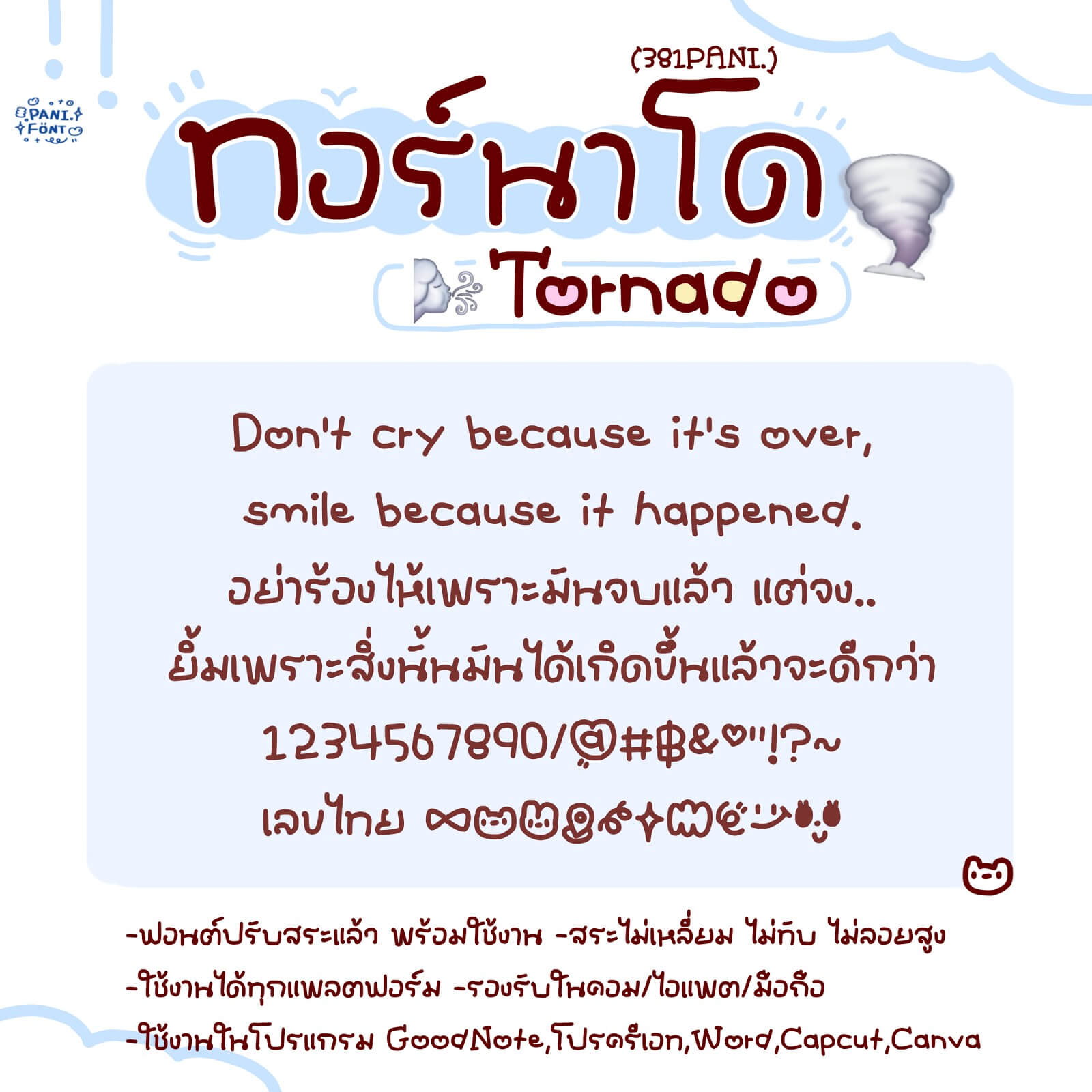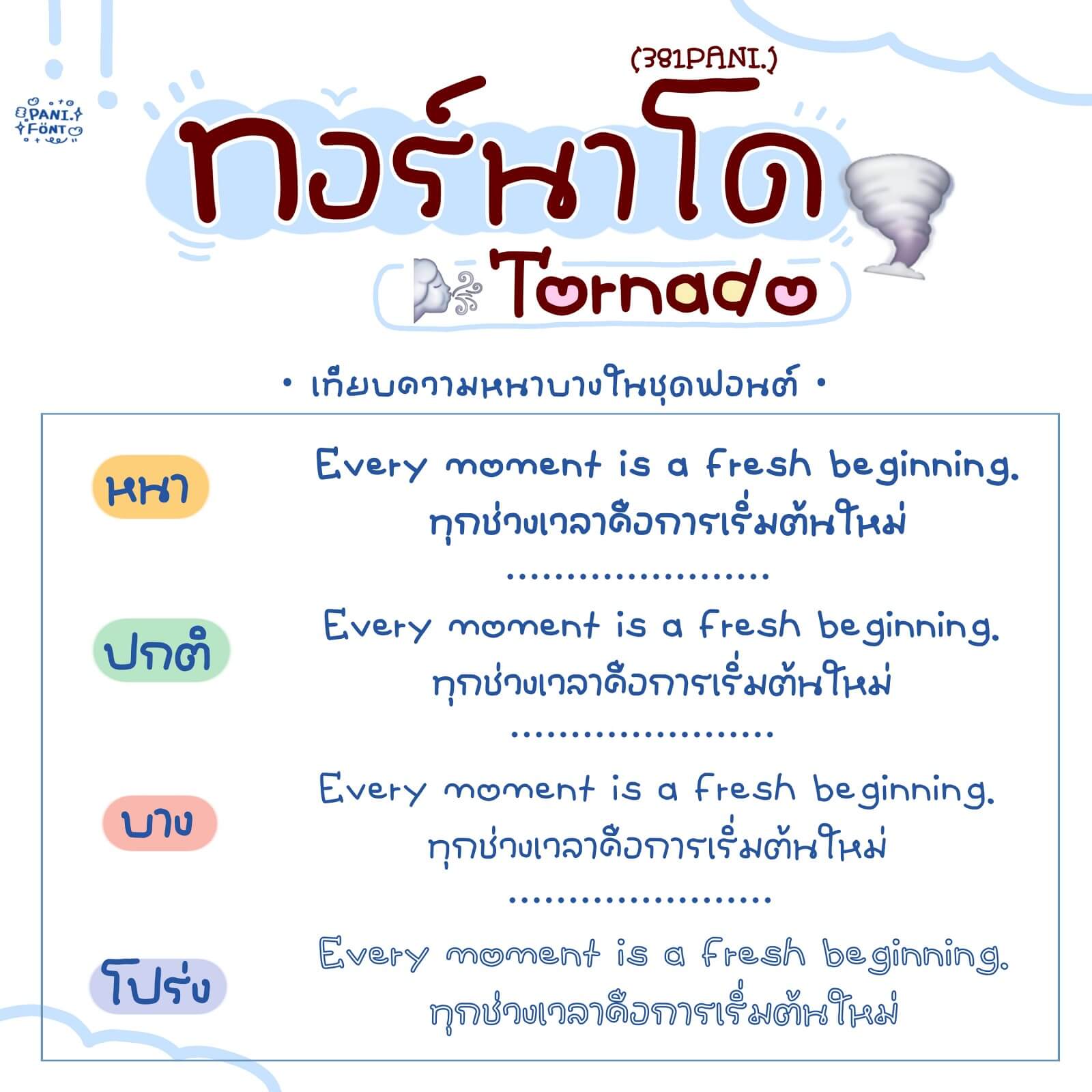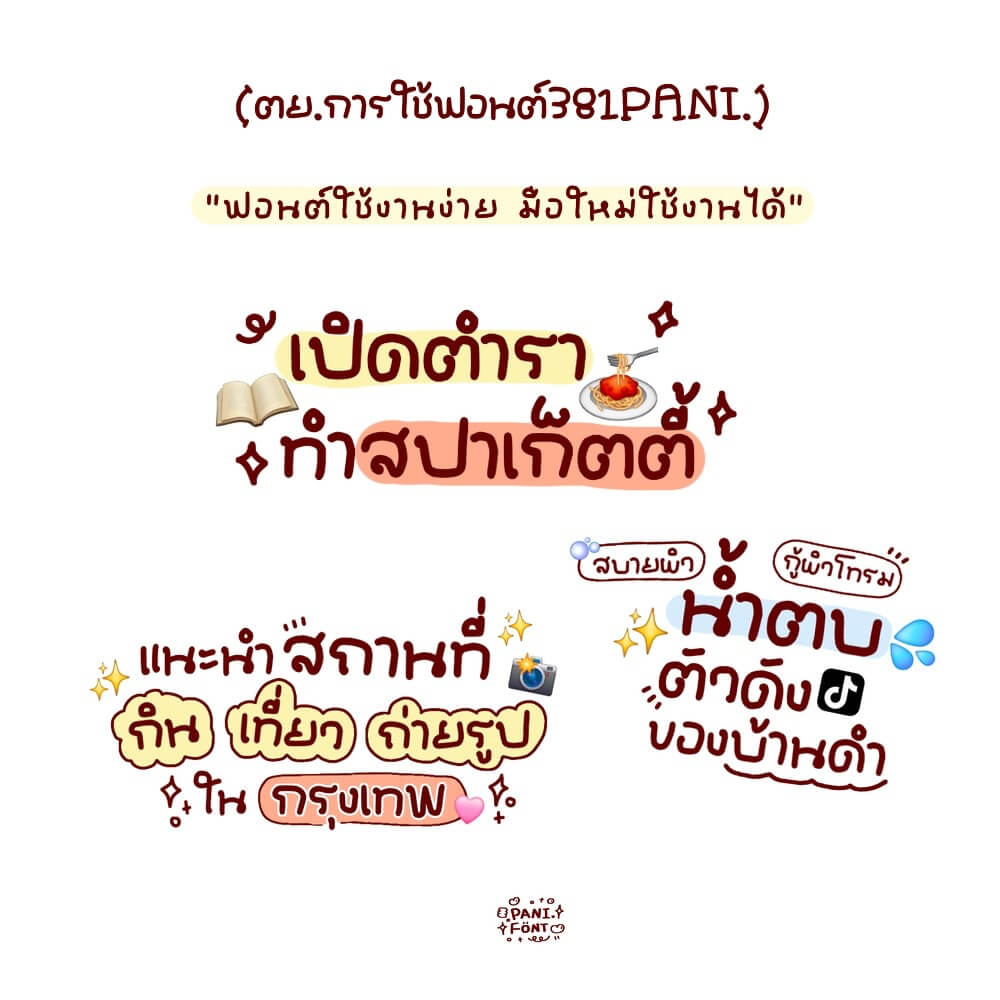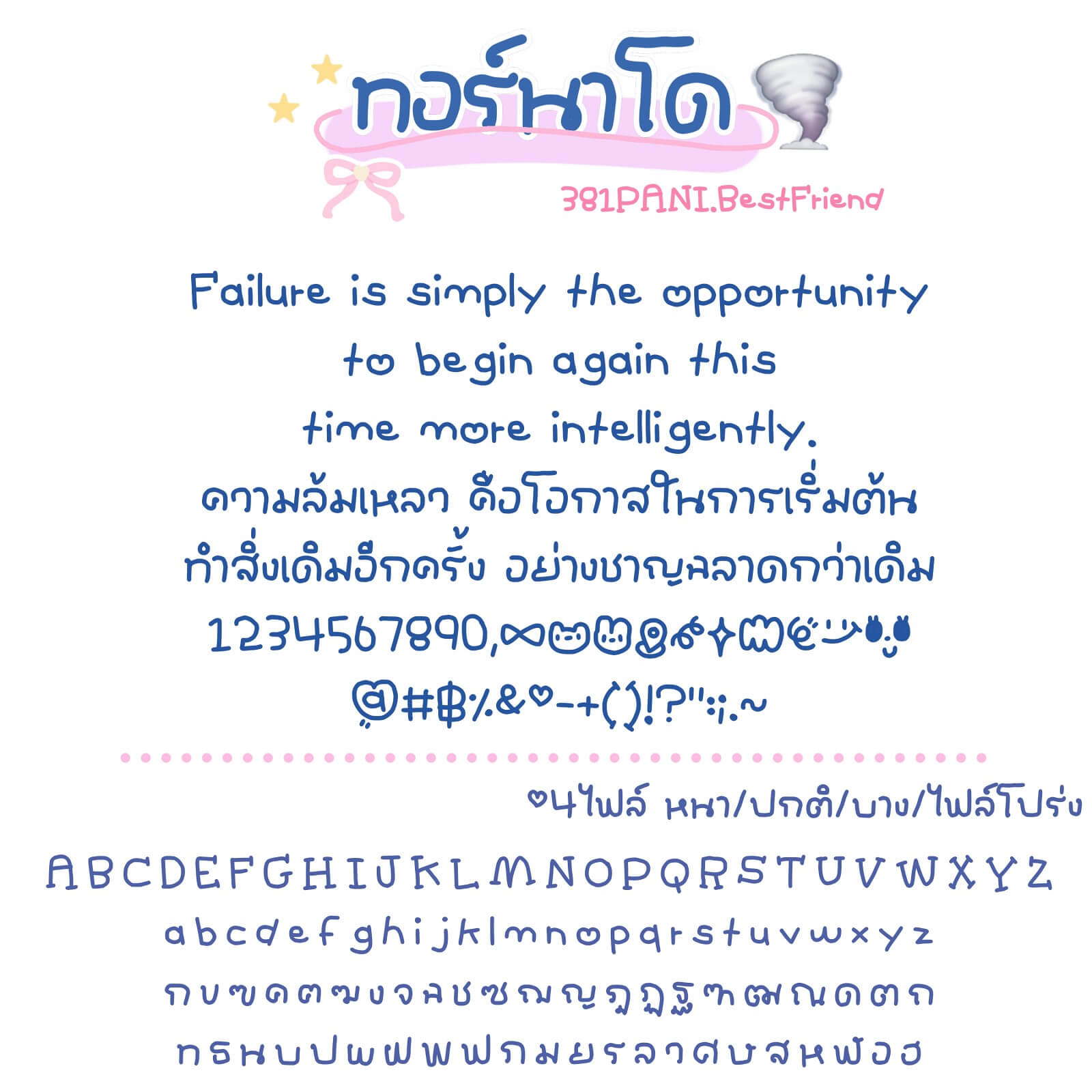
381PANI.ทอร์นาโด
ฟอนต์ 381PANI.ทอร์นาโด – ฟอนต์ไม่มีหัว แนวมินิมัล ทันสมัย สายทำคลิป แต่งภาพใช้ง่าย เหมาะกับมือใหม่ เหมือนลายมือสด เขียนเอง ตัวไม่เท่ากัน
ฟอนต์มี 4 ไฟล์ – น้ำหนัก บาง ปกติ หนา โปร่ง